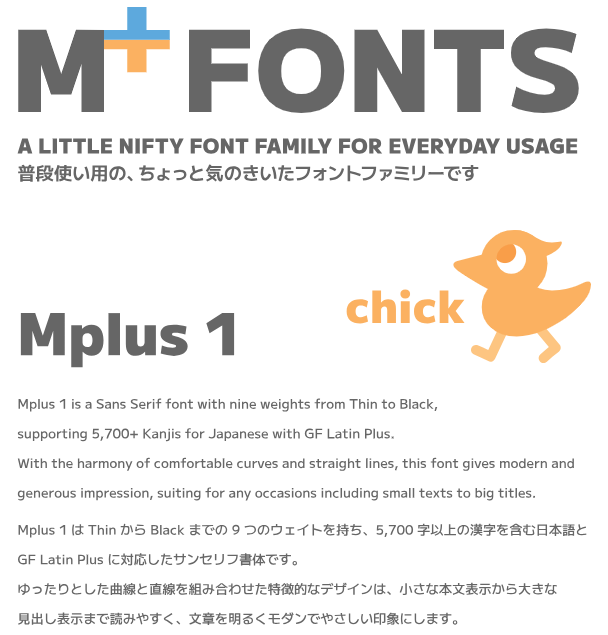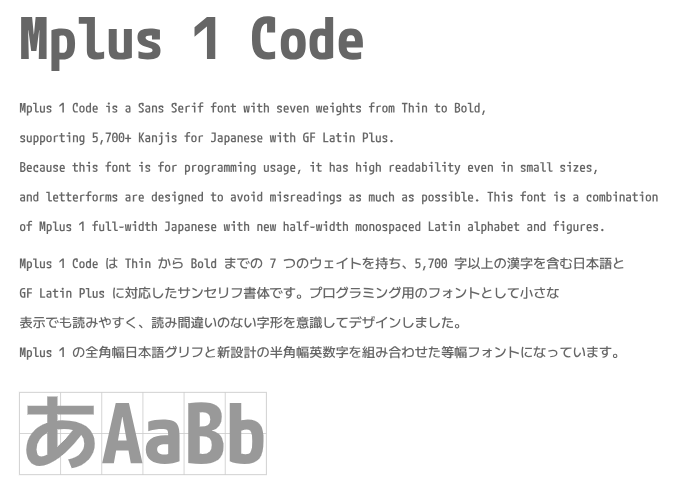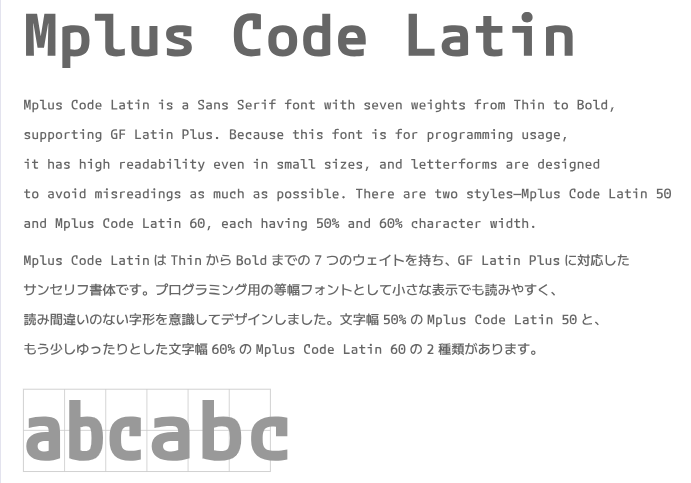
M+ FONTS 并非单一字体,而是一套免费开源的字体家族。包括了 M+ 1p / M+ 2p、M+ P Type、M+ C Type 和 M+ Kodomo 五种不同风格,是由日本设计师 Coji Morishita(森下浩司)自 2002 年起独立设计开发,目前已涵盖日文、简体/繁体中文(常用汉字及部分扩展)、拉丁字母、数字、标点符号等多种字符。
| 系列 | 特点 | 适用场景 |
|---|
| M+ 1p | 含等宽(monospace)与比例宽度版本 | 编程、终端、UI 按钮 |
| M+ 2p | 纯比例宽度,自然阅读节奏 | 网页正文、电子书、长文本 |
| M+ C Type | 强化 CJK 汉字支持 | 中日英混排文档 |
| M+ P Type | 印刷优化,细节更细腻 | 杂志、PDF、印刷品 |
| M+ Kodomo | 圆润儿童字体 | 早教材料、绘本 |